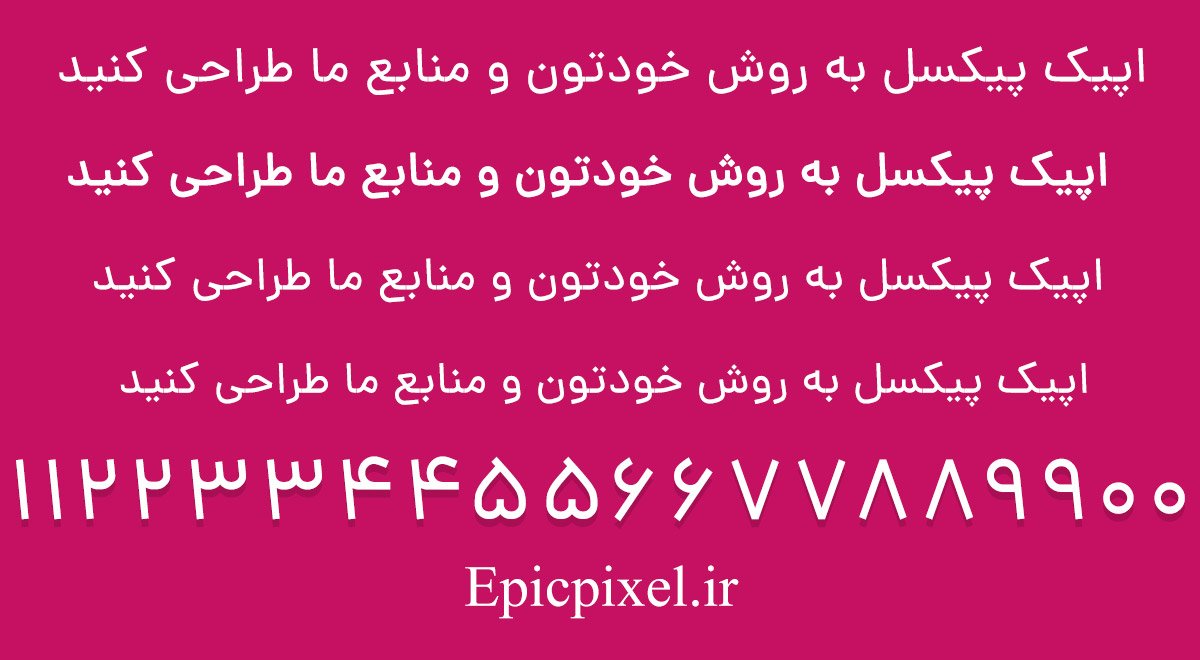
فونت دانا: یک تایپفیس هندسی و مدرن برای طراحی رابط کاربری
مقدمه فونت دانا
در دنیای امروز که تکنولوژی و ارتباطات نقش مهمی در زندگی ما دارند، طراحی رابط کاربری وب و موبایل یکی از مهارتهای مورد نیاز و پرطرفدار است. طراحان رابط کاربری باید با توجه به نیازها و انتظارات کاربران، طرحهای زیبا، کارآمد، خلاقانه و همگام با روز ارائه دهند. یکی از عناصر مهم در طراحی رابط کاربری، فونت است. فونت میتواند بسیار تأثیرگذار باشد در انتقال پیام، جذب توجه، افزایش خوانایی و ایجاد حس و حال مناسب در کاربر.
فونت دانا یک فونت هندسی و نزدیک به خط نسخ است که در خرداد ۱۳۹۸ منتشر شده و هدف آن خلق یک تایپفیس مدرن و معاصر با الهام از رسمالخط آشنای نسخ بود. فونت دانا با توجه به شکل هندسی حروف، زاویه عمودی آنها، خوشنویسی و پویایی آن، مناسب برای استفاده در طراحی رابط کاربری وب و موبایل است. همچنین فونت دانا اولین فونت فارسی است که به صورت وریبل فونت (Variable font) در ایران منتشر شده است. وریبل فونت یک تکنولوژی جدید در طراحی فونت است که به طراحان اجازه میدهد با یک فایل فونت، بتوانند از تغییرات مختلف در وزن، کشیدگی، عرض و … استفاده کنند.
طراحی حروف فونت دانا
فونت دانا یک فونت هندسی است که شکل حروف آن با ترکیب خط مستقیم و دایره شکل گرفته است. این شکل هندسی باعث میشود فونت دانا مدرن و معاصر به نظر برسد و در طراحی رابط کاربری مناسب باشد. برای مثال، حرف آ در فونت دانا با ترکیب دو خط مستقیم و یک دایره ساخته شده است. این شکل ساده و هندسی باعث میشود حرف آ در فونت دانا خوانا و شناخته شده باشد.
برای حفظ حس و حال خوشنویسی و پویایی بیشتر، راستای عمودی در فونت دانا دارای اندکی زاویه است و از خط عمودی در ترسیم حروف استفاده نشده است. این زاویه باعث میشود حروف فونت دانا نزدیک به خط نسخ باشند و در اندازه ریز و نوشتههای طولانی خوانایی آن حفظ شود. برای مثال، حرف ل در فونت دانا با ترکیب دو خط مورب ساخته شده است که زاویه آنها باعث میشود حرف ل در فونت دانا پویا و خوشنویس به نظر برسد.
علاوه بر حروف، اعداد و علائم فونت دانا هم با همین شکل هندسی طراحی شدهاند و هماهنگی بالایی با حروف دارند. این اعداد و علائم به صورت پیشفرض فارسی هستند ولی میتوانید با تغییر تنظیمات نرمافزار، از اعداد لاتین هم استفاده کنید. برای مثال، عدد ۱ در فونت دانا با ترکیب یک خط مورب و یک نقطه ساخته شده است که شباهت زیادی به حروف فارسی دارد.
خانواده وزنهای فونت دانا
فونت دانا یک خانواده سیزدهتایی است که در نسخه قبلی دارای ۱۰ وزن بود که در بازسازی جدید ۳ وزن سنگین به آن اضافه شده است. بنابراین اکنون ۱۳ وزن در دسترس است که عبارتاند از:
دانلودHairline
Thin
ExtraLight
Light
Regular
Medium
SemiBold
Bold
ExtraBold
Black
Heavy
Ultra
Fat
این وزنها به طراحان رابط کاربری اجازه میدهند با تغییر ضخامت نوشته، تأثیرات مختلف را را بر روی کاربر ایجاد کنند. برای مثال، وزن Hairline برای نوشتههای ظریف و زیبا، وزن Regular برای نوشتههای معمولی و خوانا، وزن Bold برای نوشتههای برجسته و تأکیدی مناسب است. در زیر میتوانید نمونههای مختلف از استفاده از وزنهای متفاوت فونت دانا را ببینید.
برای انتخاب وزن مناسب بسته به محتوا و مخاطب، توصیههای زیر را میتوانید در نظر بگیرید:
از وزنهای سبک برای نوشتههای ظریف، شعر، دعا، عبارات احساسی و … استفاده کنید.
از وزنهای متوسط برای نوشتههای عادی، متن، خبر، توضیحات و … استفاده کنید.
از وزنهای سنگین برای نوشتههای برجسته، عنوان، سرخط، دستورالعمل، هشدار و … استفاده کنید.
از ترکیب وزنهای مختلف برای ایجاد تنوع، تباین، تأکید و جذابیت در نوشته استفاده کنید.
وریبل فونت دانا
وریبل فونت یک تکنولوژی جدید در طراحی فونت است که به طراحان اجازه میدهد با یک فایل فونت، بتوانند از تغییرات مختلف در وزن، کشیدگی، عرض و … استفاده کنند. این تکنولوژی باعث میشود حجم فونت کم شود، سرعت بارگذاری صفحات وب افزایش یابد، قابلیت سفارشیسازی فونت به کاربر داده شود و خلاقانگی طراح را به چالش بکشد. فونت دانا اولین فونت فارسی است که به صورت وریبل فونت در ایران منتشر شده است.
وریبل فونت دانا دارای دو متغیر است که عبارتاند از:
Weight: این متغیر وزن (ضخامت) نوشته را تعیین میکند که حداقل آن ۱۰ معادل وزن Hairline و حداکثر آن ۹۹۰ معادل وزن Fat است. با تغییر این مقدار، میتوانید هر وزن دلخواه را بین حدود مشخص شده ایجاد کنید.